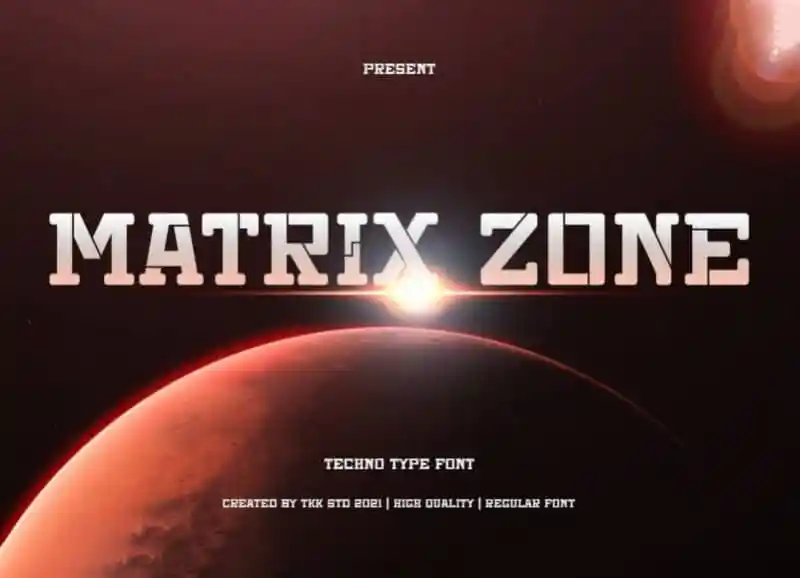
Matrix Zone Display Font – Fonte Grátis
Matrix Zone Display Font
A Matrix Zone Display Font é uma nova adição para a seleção das fontes de exibição do Tokokoo Studio, destacando-se pelo seu estilo tecnológico moderno e cut-out. Com um aspecto simples mas altamente sofisticado, ela representa uma tecnologia automática e meticulosamente elaborada que é perfeitamente adaptável para qualquer aplicação visual. Esta fonte não apenas proporciona um design elegante para elementos de exibição em banners ou websites modernos, mas também oferece a capacidade de criar uma atmosfera futurista que pode complementar designs inovadores e criativos. Ideal para designers buscando expressar seu trabalho com uma tecnologia visível e atemporal, Matrix Zone Display Font é um ótimo exemplo do poder da design gráfico no mundo digital.